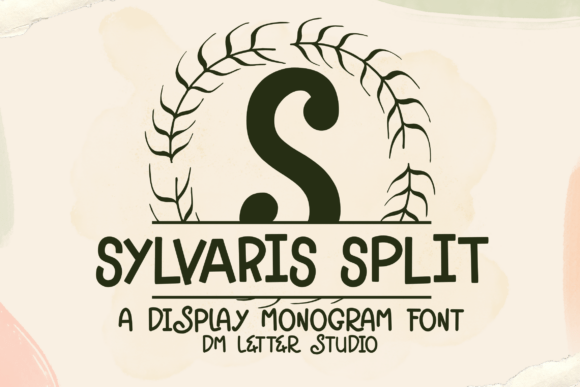
Sylvaris Split Monogram
Поиск подходящих элементов дизайна может быть сложным, но Sylvaris Split Monogram предлагает исключительную коллекцию, которая мгновенно улучшит вашу работу.
Создаете ли вы продукты POD (печать по требованию), свадебные приглашения или графику для социальных сетей, Sylvaris Split Monogram станет идеальным выбором.